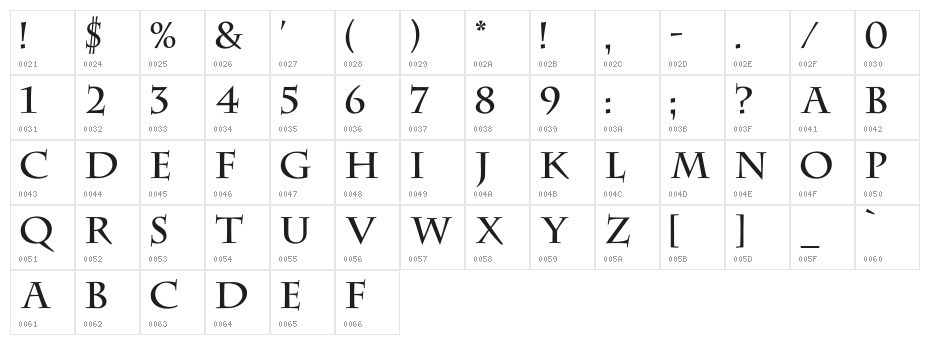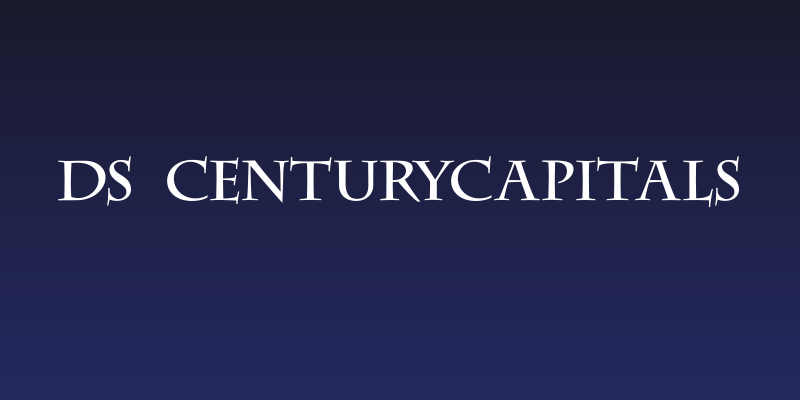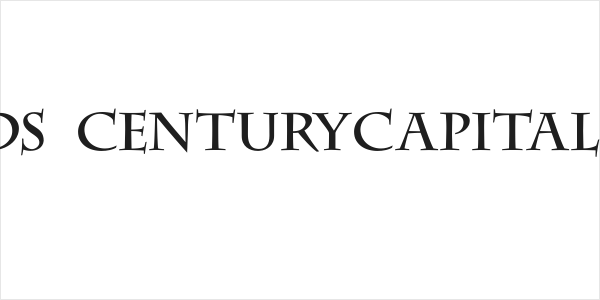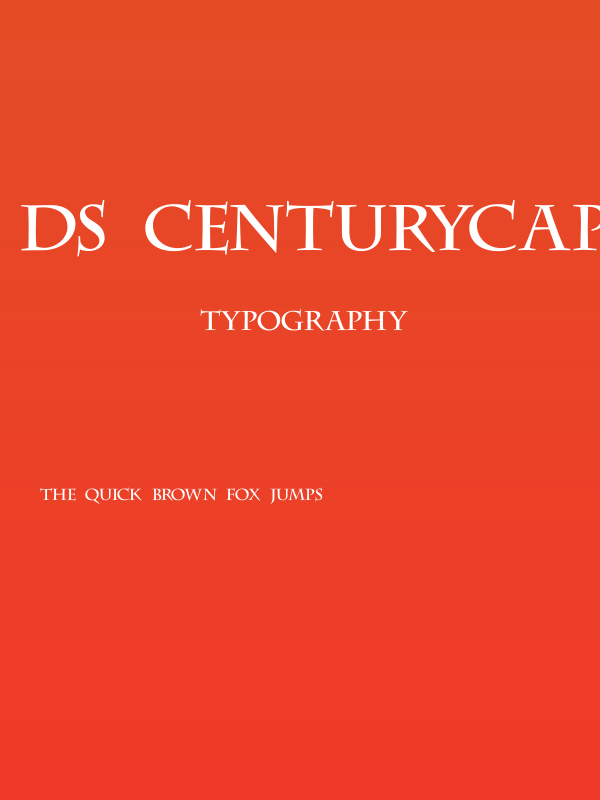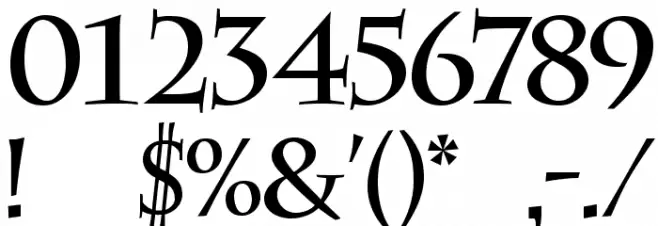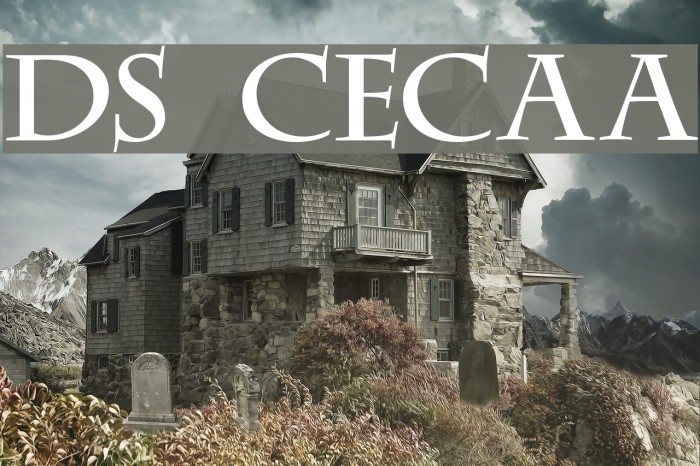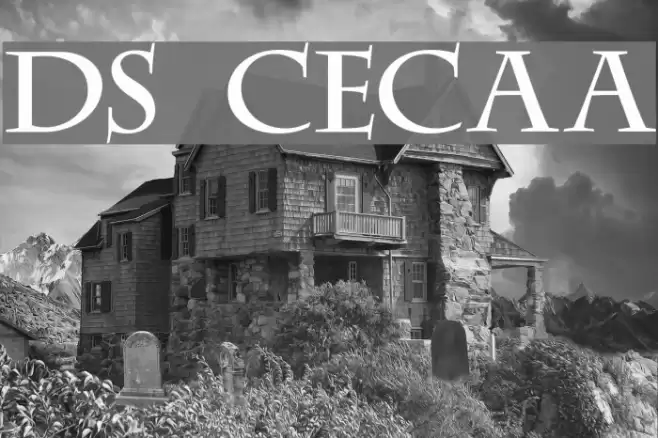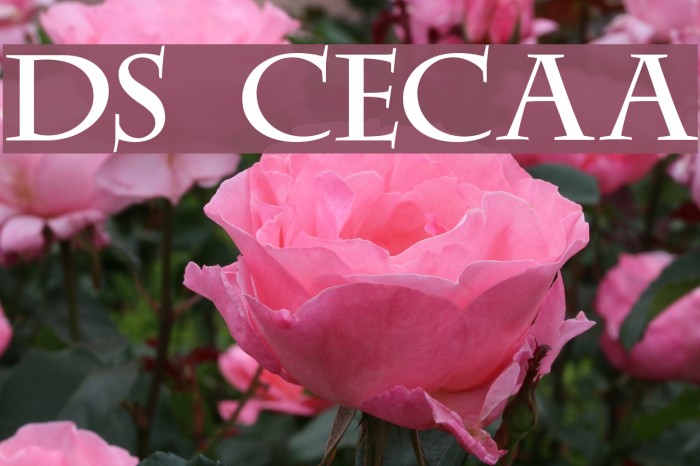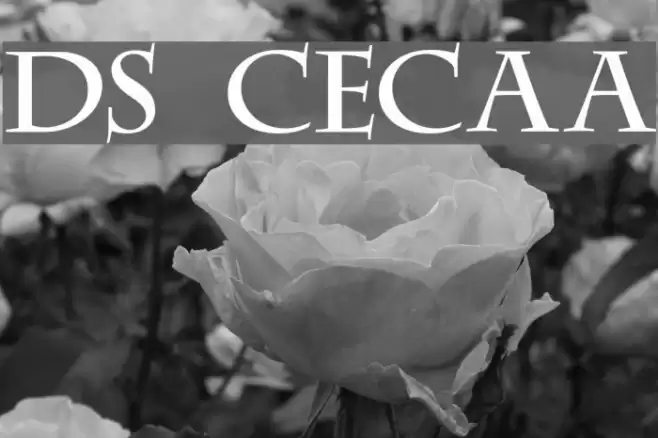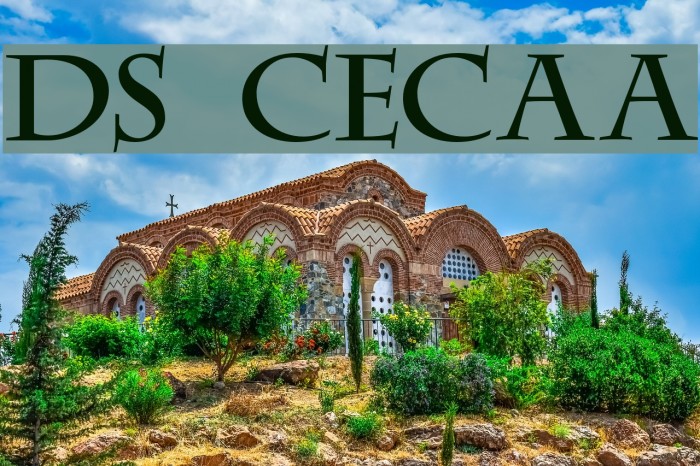
DS CenturyCapitals Font
| おすすめプロジェクト | Ideal for use in formal documents, book titles, invitations, and branding materials that require a touch of sophistication. |